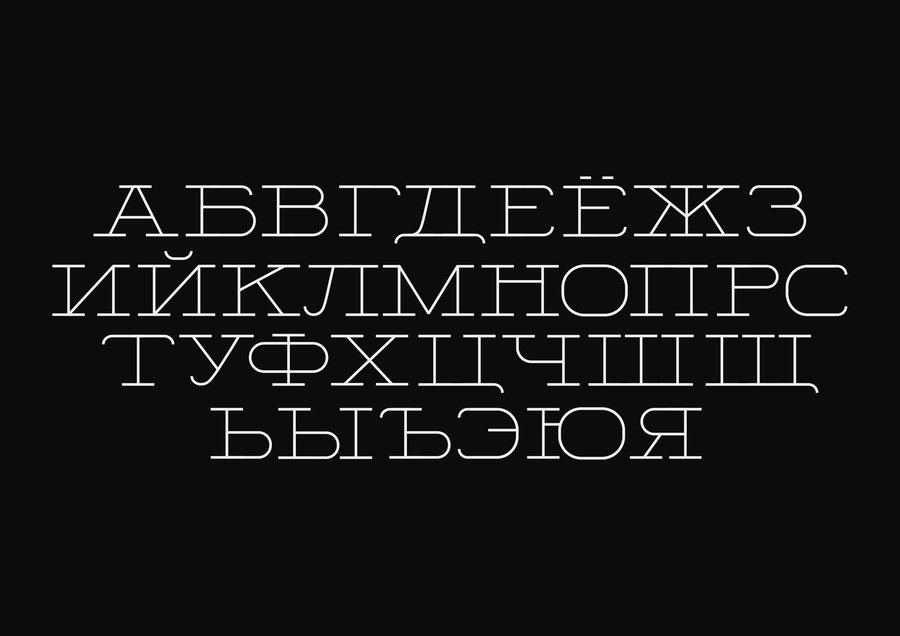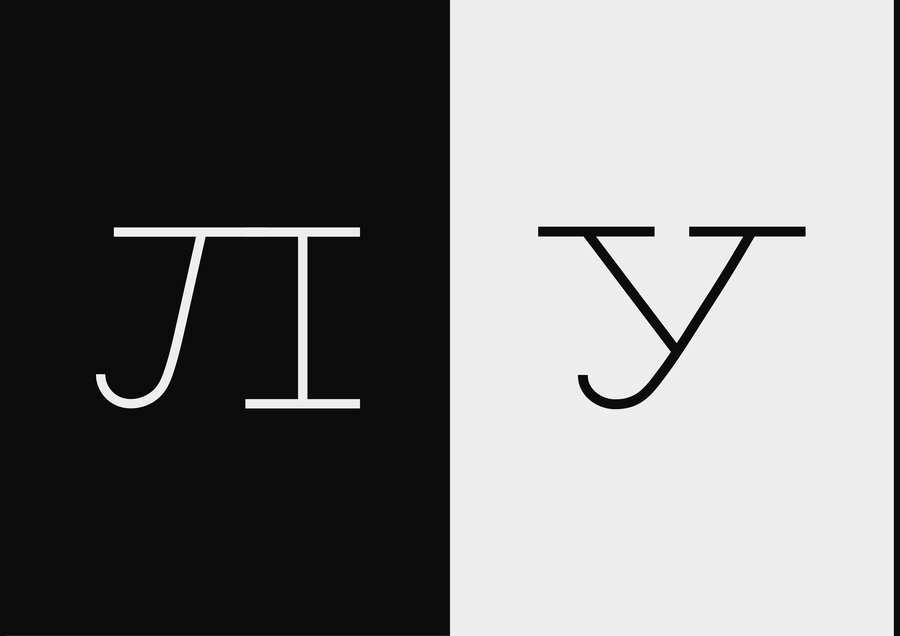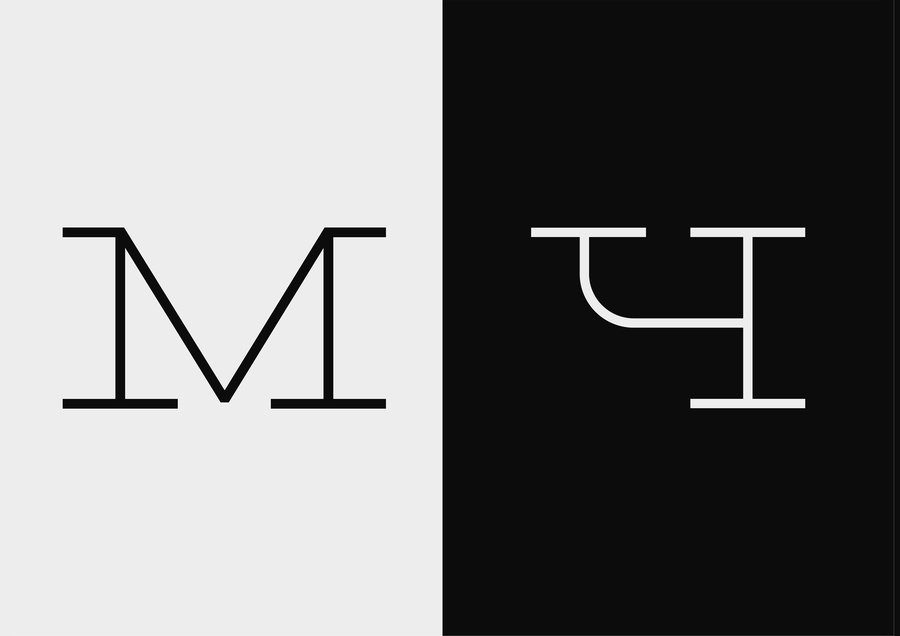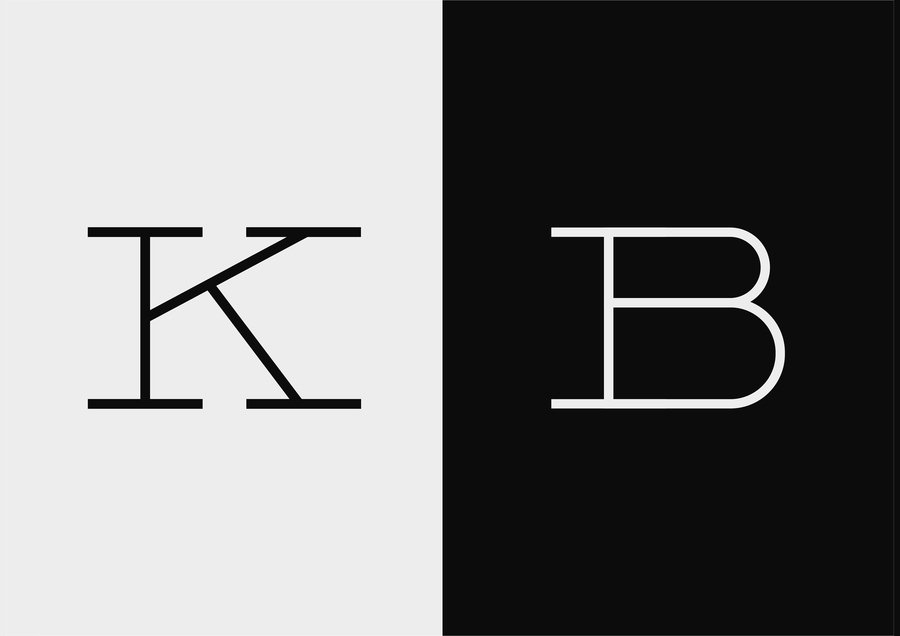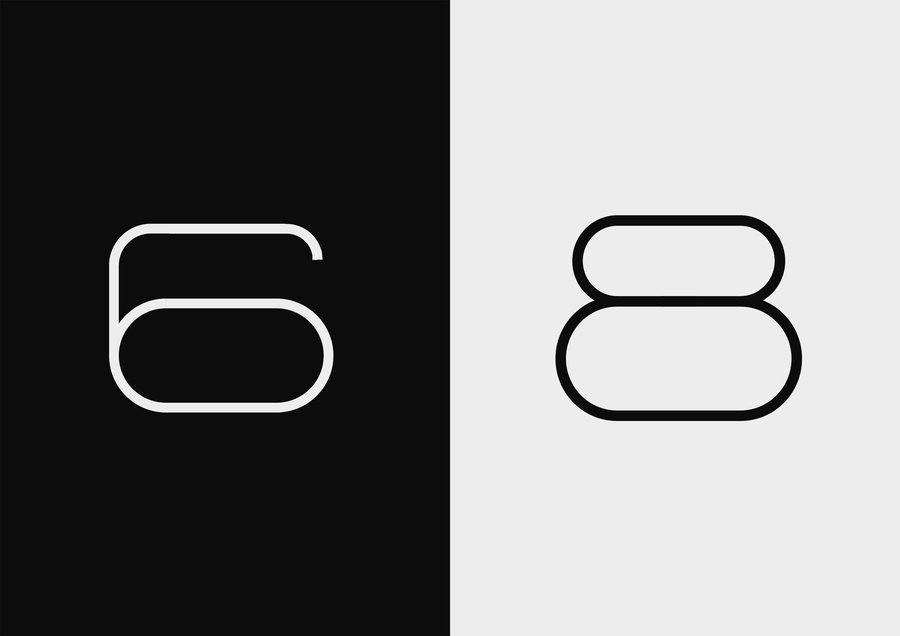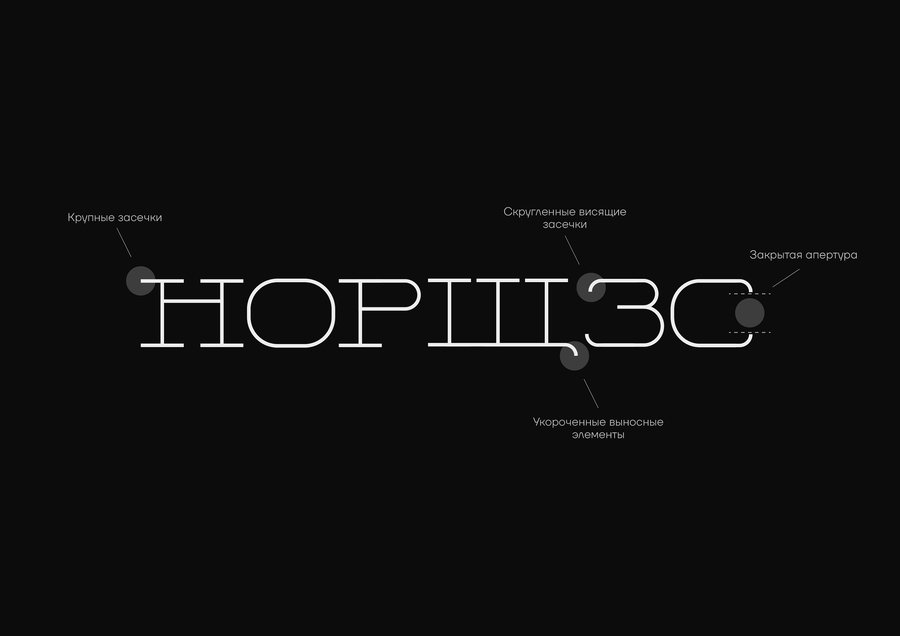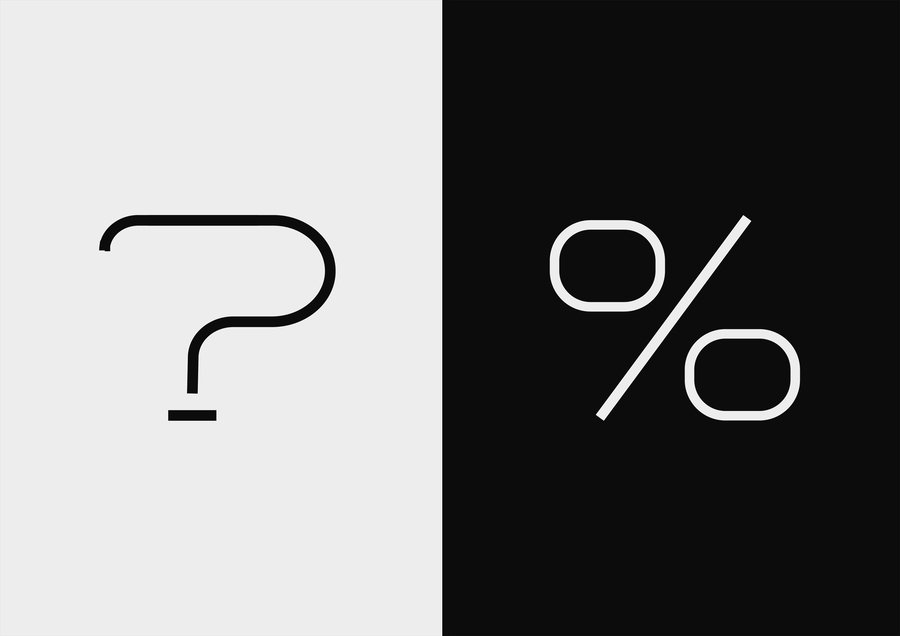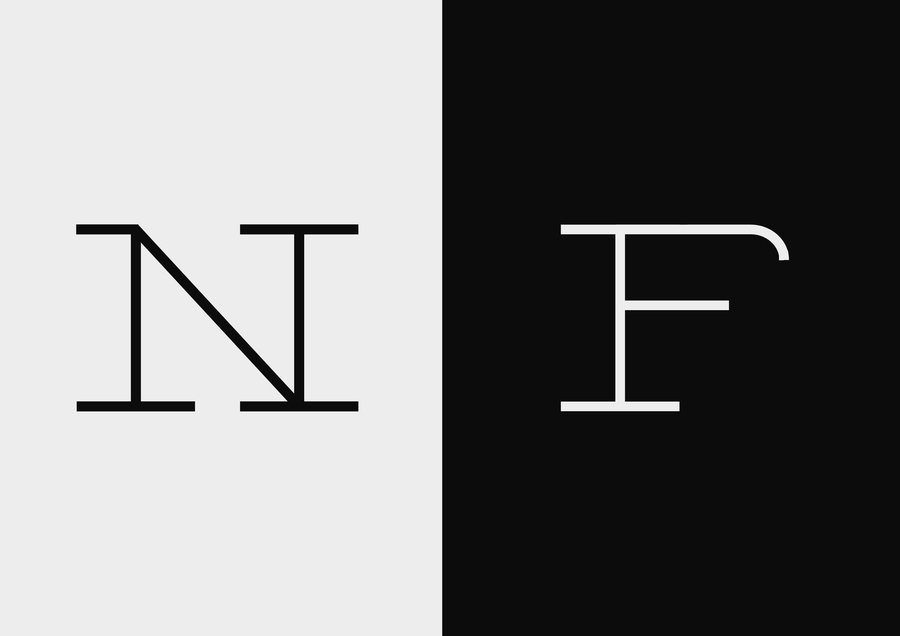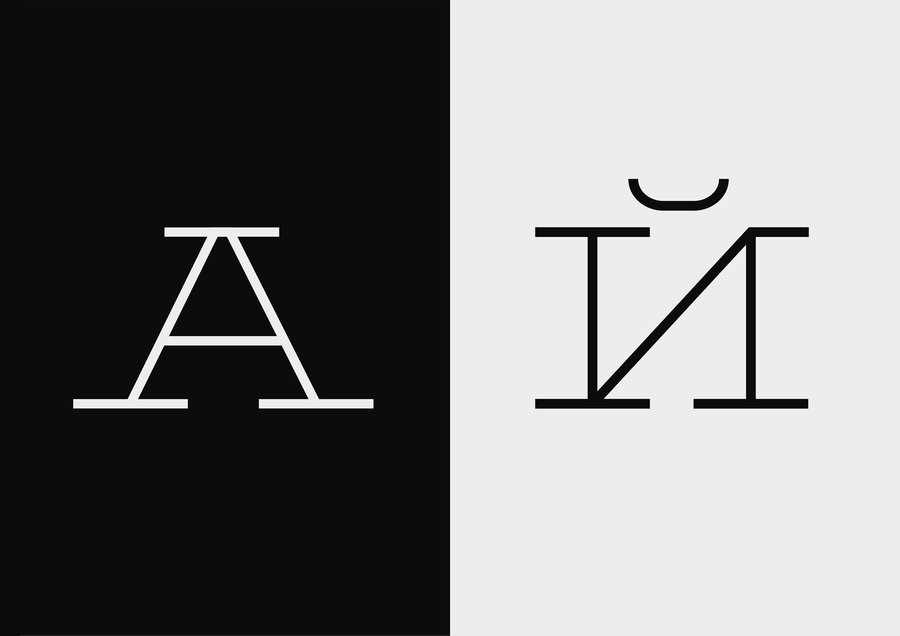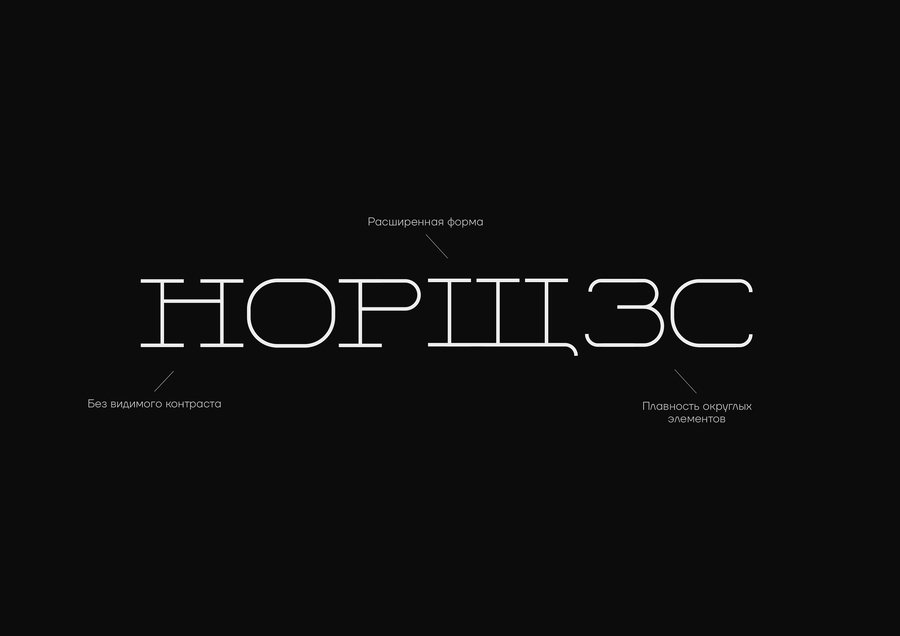
PLASTFORM FONT
Широкая геометрическая антиква с монолинейным штрихом, построенная на контрасте строгой геометрии и плавной пластики с использованием крупных засечек и скругленных форм.
Подходит для заголовков, айдентики и плакатной графики.